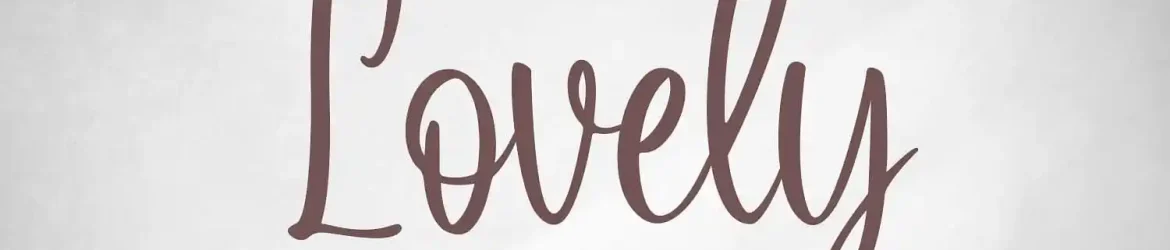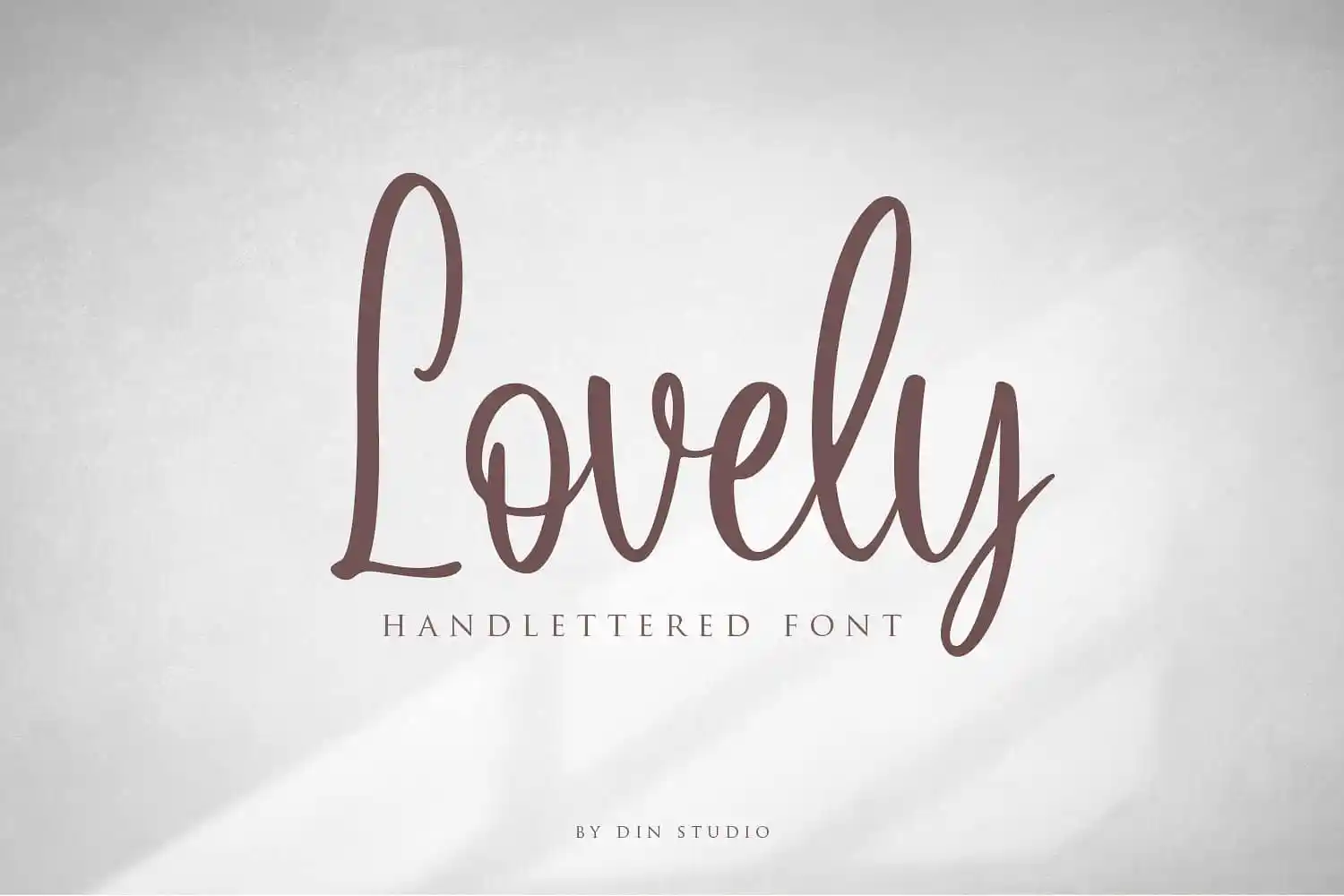
Lovely Script Font – Fonte Grátis
Lovely Script Font
Esta fonte ‘Lovely Script Font’ é uma criação moderna do Studio Din, que mescla a autenticidade natural dos traços escritos com um toque sofisticado e contemporâneo. É perfeitamente adequada para projetos de design que buscam incorporar elegância e frescura moderna ao estilo tipográfico. Seu uso ideal é em elementos como logomarcas, criação de marca, fotografias, postagens nas mídias sociais, anúncios, convites, designs de produtos, rótulos, material de papelaria, decorações casamentarias ou qualquer projeto que necessite de um toque autêntico e cuidadosamente traçado à mão. Esta fonte é uma excelente escolha para aqueles buscando criar algo atraente e personalizado.